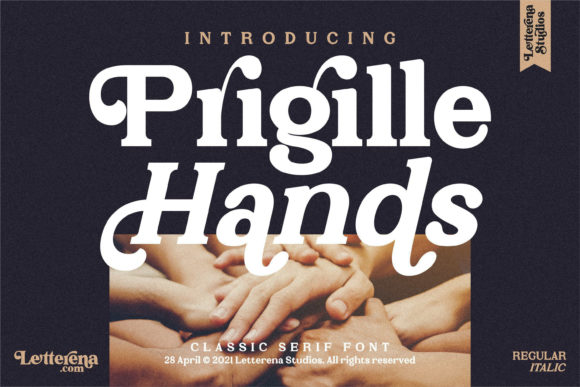
Prigille Hands - смелый, модный и универсальный шрифт с засечками.
Его можно легко добавить в различные дизайнерские идеи, как формальные, так и неформальные.
Этот шрифт был создан специально для тех, кому нужен красивый и освежающий вид их дизайна.